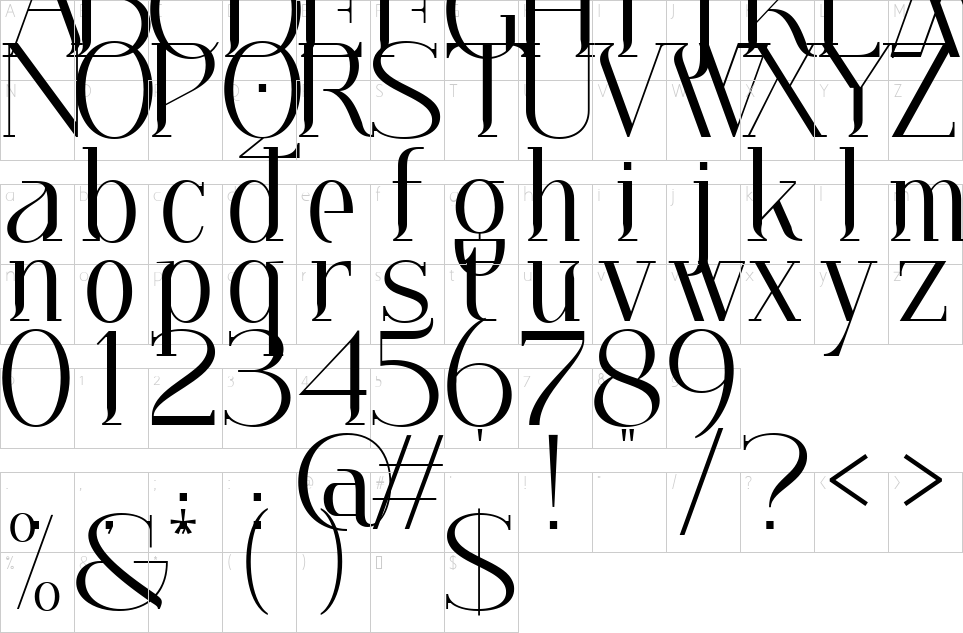
A fonte Mitoga Display oferece uma paleta de caracteres elegante e versátil, perfeita para qualquer projeto que exige um toque sofisticado e limpo. Desenhada pela equipe de design Areatype, a fonte Mitoga Display é uma escolha ideal para quem busca uma solução gráfica que combine modernidade com uma atmosfera nostálgica. Composta por linhas retas e linhas finas com sutis detalhes, a Mitoga Display é perfeita para headlines, marcas e qualquer texto que deseja um impacto visual único. Seja para um site de design minimalista ou um banner de marketing, a Mitoga Display não decepciona. Com facilidade de uso para tanto Windows quanto Mac, essa fonte gráfica gratuita é uma ótima maneira de adicionar um toque único a qualquer projeto.